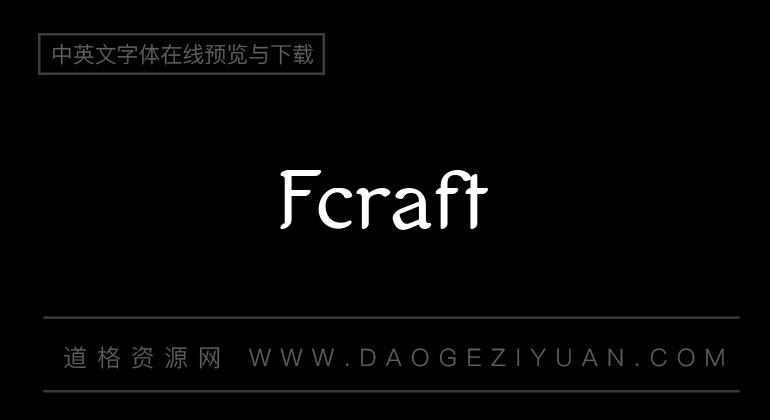
Fcraft
Fcraft 字体是一款设计师非常喜爱的字体,它受到了众多设计师们的追捧。Fcraft 字体以其独特的外观,柔和的线条和精致的细节而闻名,它可以提供非常优美的视觉效果,是一款非常适合用于各种设计创作的字体。Fcraft 字体可以满足各种不同的设计需求,它可以用于海报、商标、书籍封面、网站、品牌标识等等,为设计师提供极具创意的设计素材。
Fcraft是一款非常不错的手写艺术字体,具有很好的视觉感,适合于文化类的宣传设计、商业类品牌的广告和产品包装设计以及个性化文字排版等较多场景。